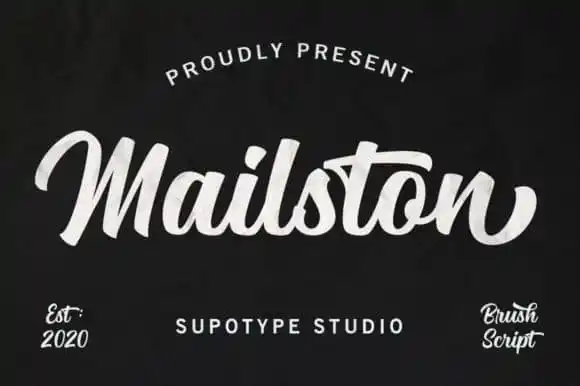
Mailston Script Font – Download Grátis
A Mailston Script Font é uma deliciosa tipografia script vintage criada pela supotype que ganhou um toque adoravelmente fofo. Ela traz ligaturas e alternativas de letras para oferecer ainda mais personalidade ao seu design. Esse estilo retrô vem em forma de fonte, permitindo que você faça uma belíssima arte tipográfica. E é perfeito para se juntar a qualquer projeto de desenho que esteja à procura de um toque nostálgico e encantador. Para aqueles que buscam uma fonte criativa para dar um toque especial em suas produções, a Mailston Script Font está aqui para atendê-los.